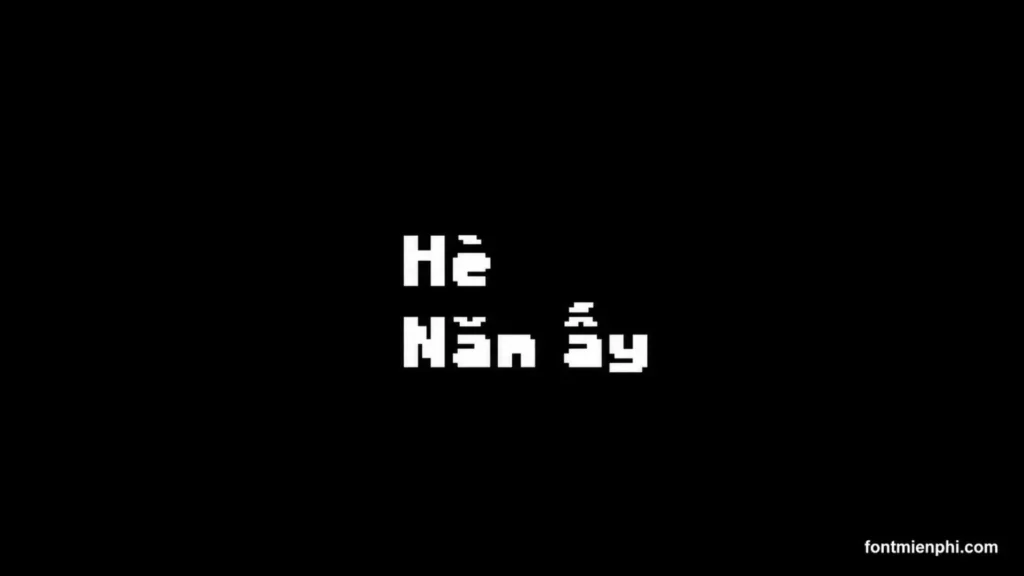
Tải Font Việt Hóa Amenory Bold – Phông Chữ Mạnh Mẽ, Hiện Đại Cho Thiết Kế Đỉnh Cao
Trong lĩnh vực thiết kế đồ họa, việc lựa chọn một phông chữ (font) phù hợp đóng vai trò quyết định đến sự thành công của một ấn phẩm. Nếu bạn đang tìm kiếm một kiểu chữ vừa có độ nét dày dặn, ấn tượng nhưng vẫn giữ được sự tinh tế và hiện đại, thì Font Việt hóa Amenory Bold chính là sự lựa chọn hoàn hảo.
Tải Font Việt Hóa Amenory Bold – Phông Chữ Mạnh Mẽ, Hiện Đại Cho Thiết Kế Đỉnh Cao
1. Giới thiệu tổng quan về Font Việt Hóa Amenory Bold
Amenory Bold là một trong những phông chữ mang đậm phong cách hiện đại, thanh lịch nhưng không kém phần mạnh mẽ nhờ định dạng nét đậm (Bold). Với cấu trúc các chữ cái được thiết kế tỉ mỉ, khoảng cách (kerning) cân đối, font chữ này dễ dàng tạo ra sức hút thị giác cực lớn ngay từ cái nhìn đầu tiên.
Phiên bản Font Việt hóa Amenory Bold đã được các nhà thiết kế tinh chỉnh lại bộ dấu câu tiếng Việt một cách cẩn thận. Các dấu hỏi, ngã, nặng, sắc, huyền được thiết kế đồng bộ với đường nét nguyên bản, giúp bạn gõ tiếng Việt có dấu mượt mà trên mọi phần mềm thiết kế mà không lo tình trạng lỗi font hay lệch nét.
Những ưu điểm nổi bật của Amenory Bold:
• Đường nét sắc sảo, dày dặn: Rất thích hợp để tạo điểm nhấn mạnh mẽ.
• Hỗ trợ tiếng Việt 100%: Bản Việt hóa chuẩn, dấu câu hài hòa với ký tự gốc.
• Tính linh hoạt cao: Phù hợp với cả thiết kế in ấn lẫn thiết kế kỹ thuật số (Digital design).
2. Ứng dụng thực tế của Font Amenory Bold trong thiết kế
Với sắc thái mạnh mẽ nhưng đầy tính nghệ thuật, Font Việt hóa Amenory Bold là “trợ thủ đắc lực” cho rất nhiều dạng dự án khác nhau:
2.1. Thiết kế Logo và Bộ nhận diện thương hiệu
Nhờ form chữ cứng cáp, rõ ràng, Amenory Bold đặc biệt phù hợp để thiết kế logo cho các thương hiệu thời trang, công nghệ, bất động sản hoặc mỹ phẩm cao cấp. Chữ in đậm giúp tên thương hiệu nổi bật, dễ nhớ và thể hiện sự chuyên nghiệp, uy tín.
2.2. Thiết kế Tiêu đề (Heading), Poster và Banner
Nếu bạn cần một font chữ để làm tiêu đề chính trên các Poster quảng cáo, Banner Facebook, hay ảnh Thumbnail YouTube, Amenory Bold sẽ làm xuất sắc nhiệm vụ thu hút ánh nhìn. Khả năng hiển thị tuyệt vời của phông chữ này giúp thông điệp của bạn “đập” ngay vào mắt người xem.
2.3. Ấn phẩm truyền thông & Tạp chí
Font cũng rất được ưa chuộng trong việc thiết kế trang bìa tạp chí, layout sách báo hoặc các ấn phẩm lookbook nhờ sự hòa quyện giữa nét hiện đại và sang trọng.
4. Lời kết
Font Việt hóa Amenory Bold thực sự là một phông chữ chất lượng, đa dụng và không thể thiếu trong kho tài nguyên của bất kỳ Designer nào. Từ những dự án thiết kế mang tính mạnh mẽ, cá tính cho đến những ấn phẩm cần sự sang trọng, Amenory Bold đều có thể đáp ứng một cách trọn vẹn.